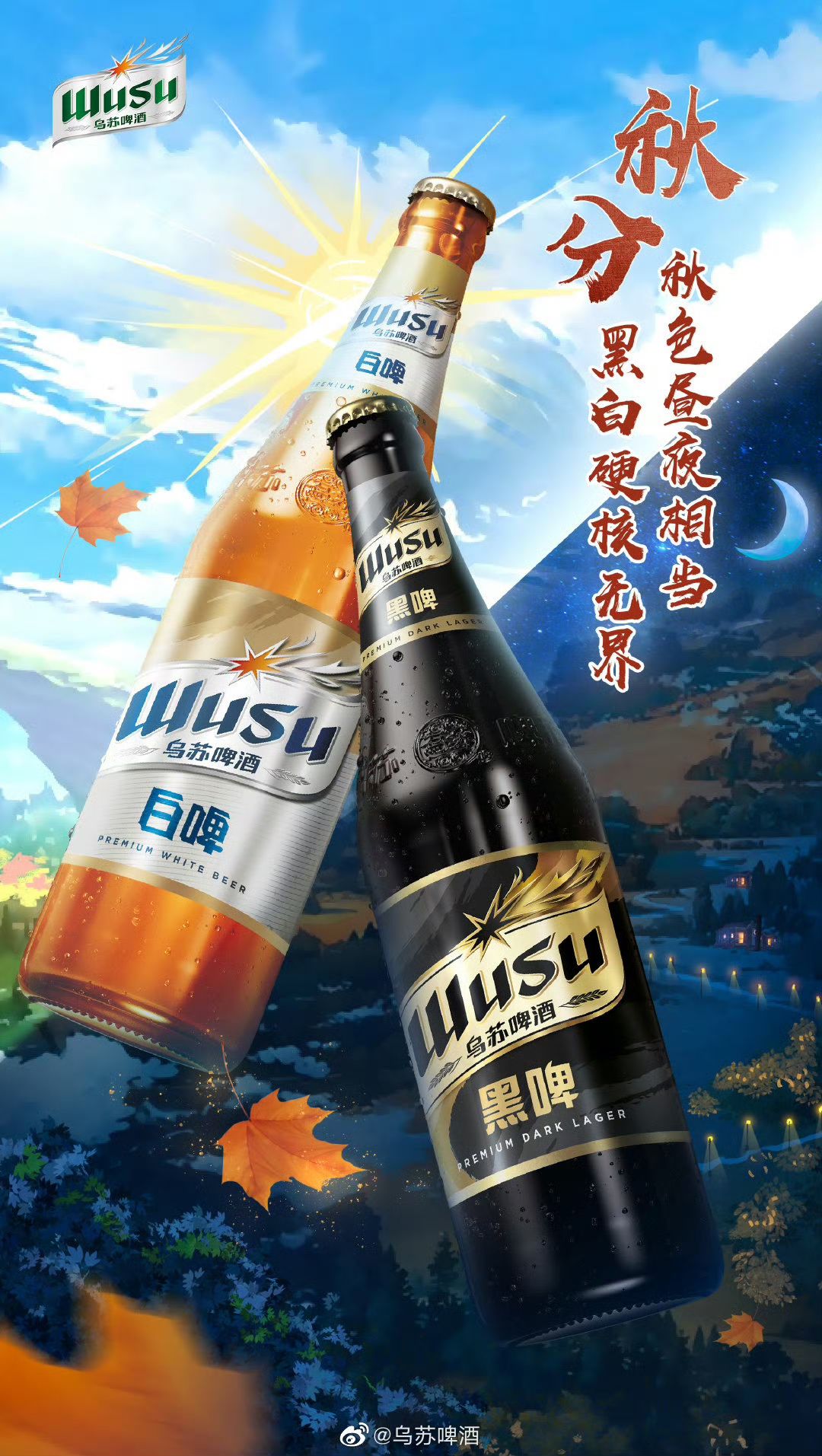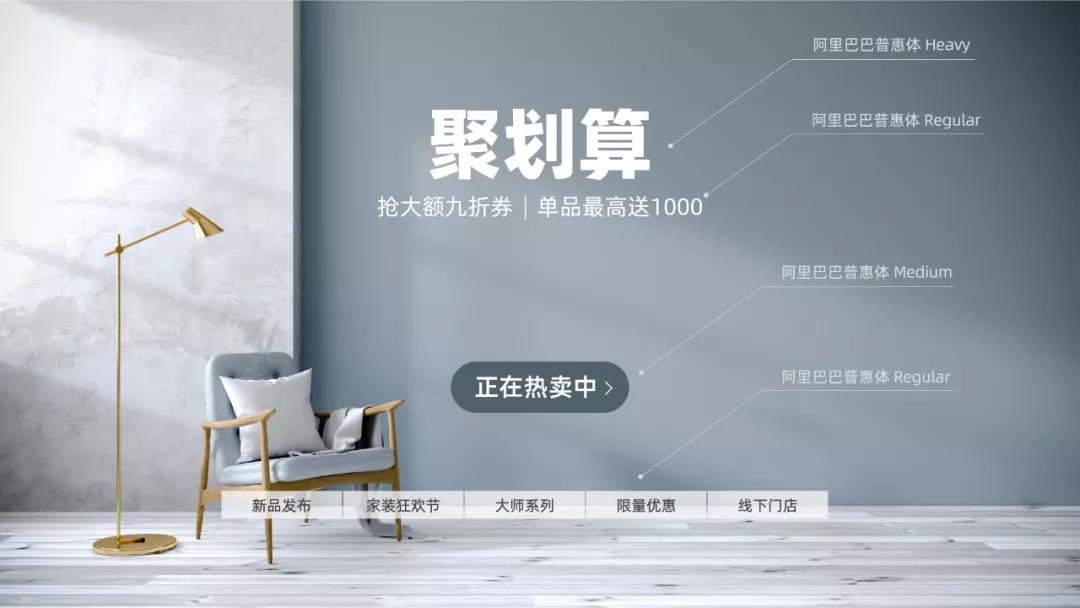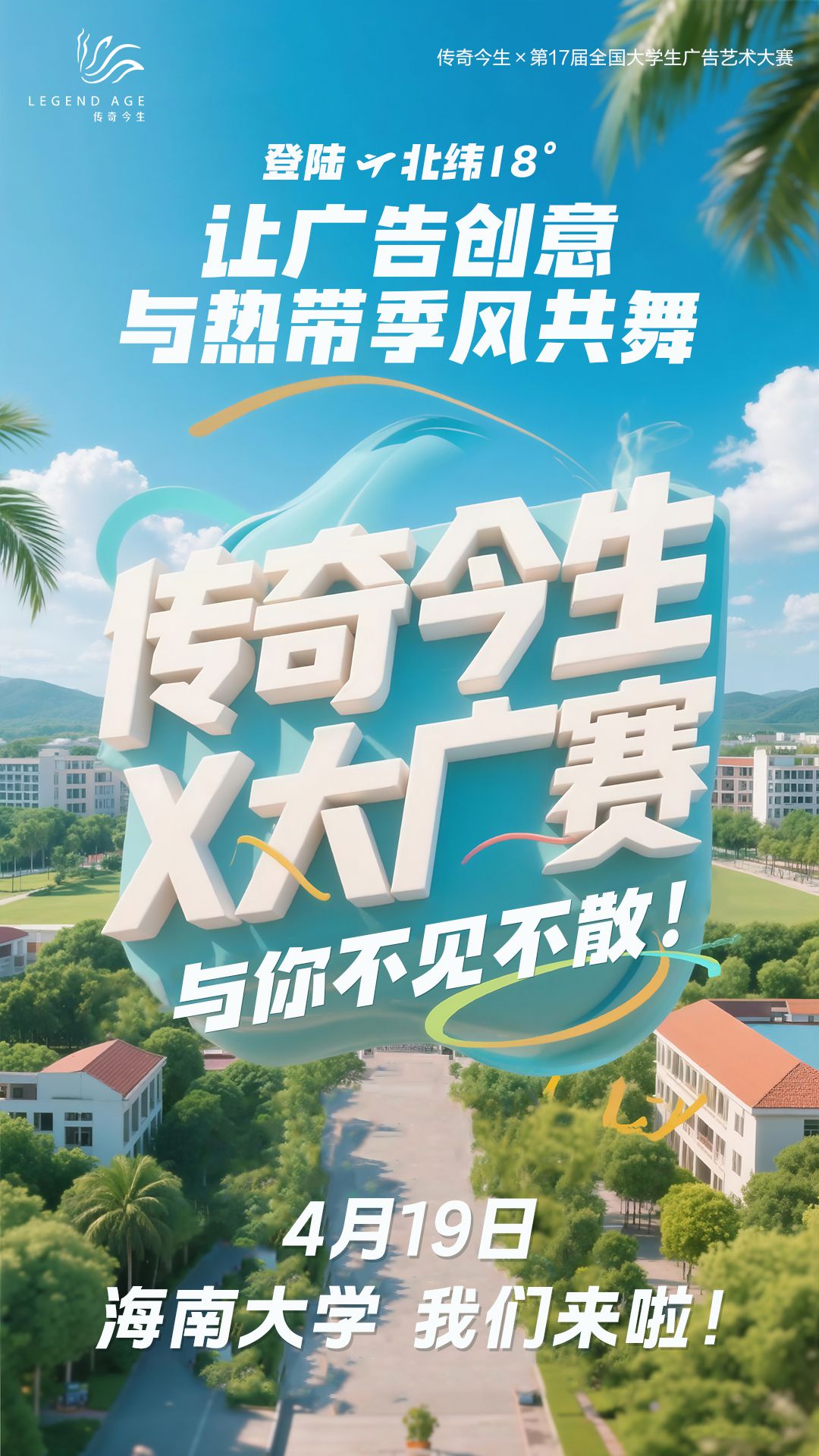
2026年电商设计字体趋势:高效精准的视觉沟通
在信息快速流转的电商环境中,2026年的字体应用正朝着更高效、更精准的方向发展。核心趋势是:字体作为“视觉情绪触发器”和“信息效率工具”的双重属性被极致放大。设计师将更依赖少量但功能分明的字体组合,以在瞬间完成品牌调性传递与信息清晰传达。
一、趋势洞察:精准表达与效率至上
1. 情绪化表达:极具个性与手工感的字体被用于关键触点,旨在快速激发情感共鸣,打破模板化设计。
2. 功能化基石:高度清晰、多语言适配的免费商用字体成为支撑海量内容的基础,确保可靠与普适。
3. 场景化匹配:字体选择与产品品类、营销场景深度绑定,成为直观的“产品语言”。
二、核心字体推荐与应用解析
1. 汉仪尚巍手书:情绪引爆器
核心特征:一款笔触粗犷、充满原始张力的手写字体,是制造视觉冲击、表达热情与个性的首选。
场景与案例:适用于需要强情绪感染力的场景。
使用要诀:仅用于核心标题或短句,给予足够空间,避免用于正文。
2. 阿里巴巴普惠体:全能系统基石
核心特征:字重丰富、字形清秀的免费商用字体家族,涵盖多国语言,是构建统一、专业视觉系统的可靠基础。
场景与案例:适用于全平台正文、多语言信息及长效品牌形象。
使用要诀:利用其丰富字重(如用Heavy做标题,Regular做正文)建立清晰的视觉层级。
3. 优设标题黑:功能强化先锋
核心特征:字形方正、结构稳重的免费商用标题字体,具有极佳的视觉聚拢感和高可读性,能有效传递信心与力量。
场景与案例:适用于需要突出功能、价格或科技感的场景。
使用要诀:专门用于标题与关键卖点,搭配柔和字体形成对比,字号不宜过小。
结语
2026年,高效的电商字体策略在于精准的“组合拳”:“汉仪尚巍手书”用于制造记忆点,“优设标题黑”用于强化信息点,“阿里巴巴普惠体”则作为承载一切信息的基座。掌握这套逻辑,并善用字由等工具进行管理,能让设计在合规的前提下,以最低的认知成本实现最大的沟通效能。